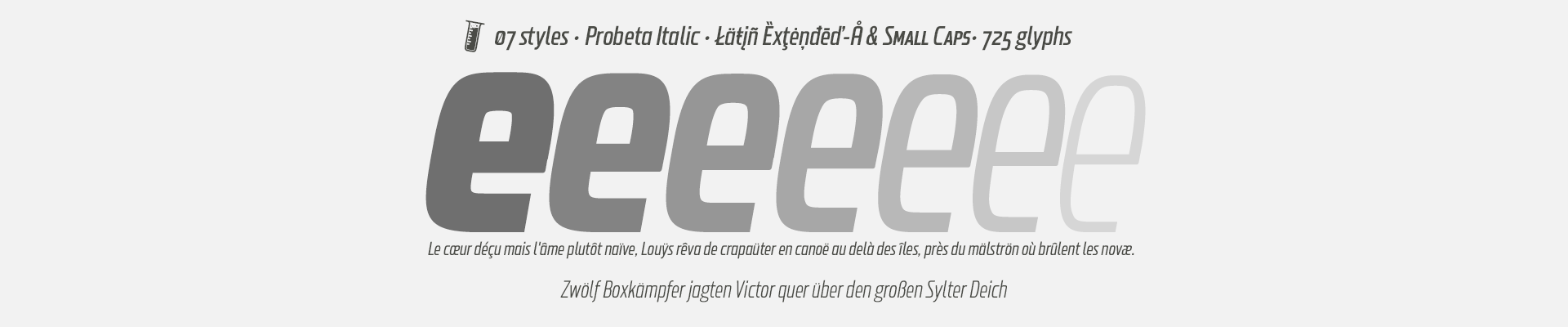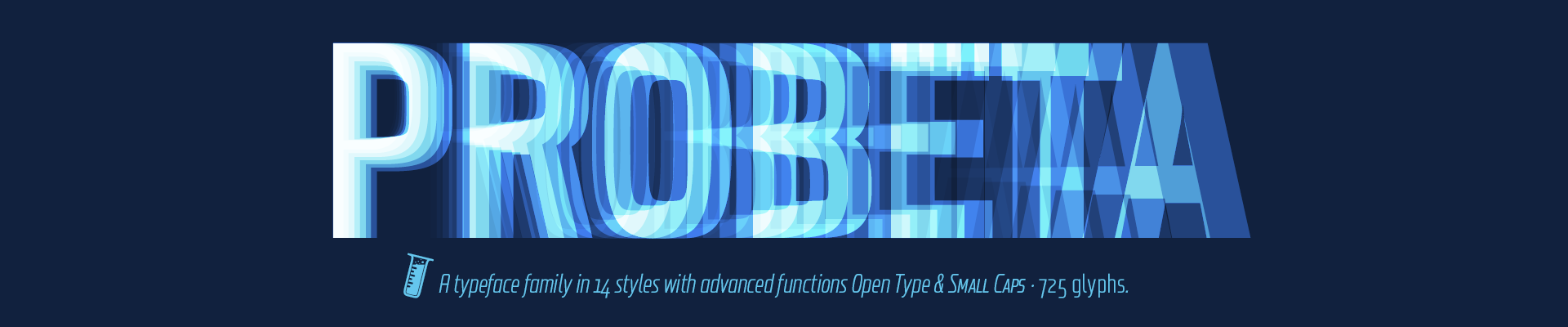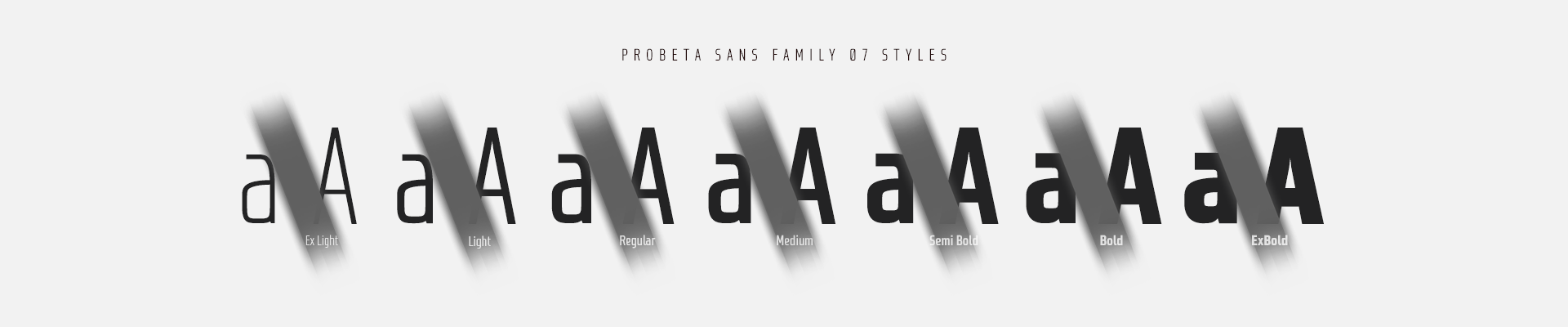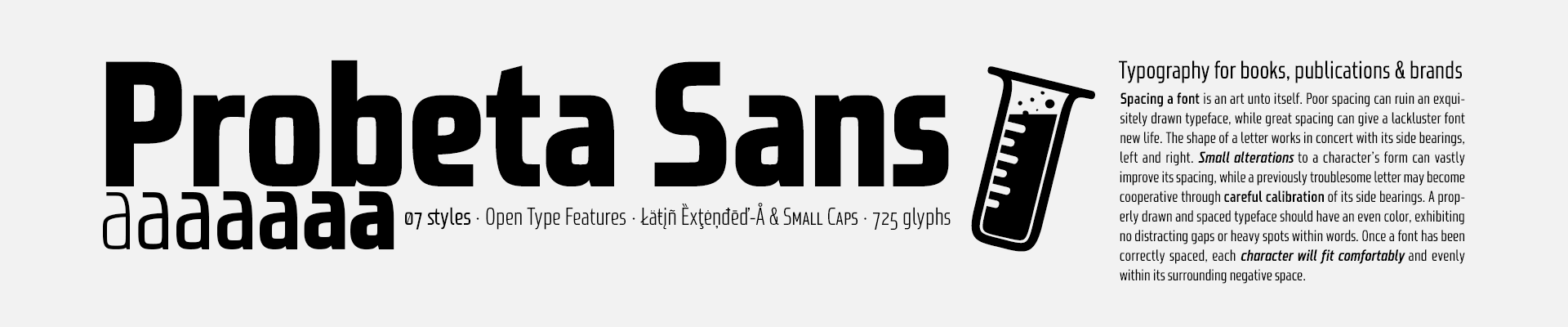
Después de definir todas las proporciones de la nueva tipografía, y partir del dibujo de la letra «o» minúscula, en un ejercicio de construcción minimalista, he construido todos los caracteres, aportando con esta técnica, coherencia morfológica y una lectura equilibrada. He puesto especial interés en la definición de la anchura de cada carácter, en función de la relación con otros, a continuación, la configuración de las métricas y la exhaustiva definición del Kerning, aportan máxima legibilidad en textos de párrafo y títulos.
Todas las versiones tienen caracteres en Versalita, letras alternativas, varios juegos de números y funciones avanzadas OpenType.
Estilo: Sans Serif, Condensed, Small Caps, Roman & Italics
Proporción: Extra Light, Light, Regular, Medium, Semi Bold, Bold & Extra Bold
Glyphs: 725
Alternates: 70
Latin-Extended: Latín Básico, Europa Occidental, Central & Oriental.
Funciones OpenType: Additional languages, All Alternates, Alternate Annotation Forms, Bitcoin, Capital Spacing, Contextual Alternates, Denominators, Discretionary Ligatures, Extended Fractions, Historical Forms, Inferiors, Kerning, Localized Forms, Numerators, Oldstyle Figures, Ordinals, Scientific Inferiors, Slashed Zero, Small Capitals, Small Capitals From Capitals, Standard Ligatures, Stylistic Set, Subscript, Superior letters, Superiors, Superscript.
Después de definir todas las proporciones de la nueva tipografía, y partir del dibujo de la letra «o» minúscula, en un ejercicio de construcción minimalista, he construido todos los caracteres, aportando con esta técnica, coherencia morfológica y una lectura equilibrada. He puesto especial interés en la definición de la anchura de cada carácter, en función de la relación con otros, a continuación, la configuración de las métricas y la exhaustiva definición del Kerning, aportan máxima legibilidad en textos de párrafo y títulos.
El uso en diseño gráfico, editorial o publicidad garantiza originalidad y diferencia. Unas fuentes muy versátiles para carteles publicitarios, vídeo juegos, títulos de cine, logotipos, publicaciones, etc. Incluyen el símbolo del Bitcoin y otras Cripto Monedas.
Todas las versiones tienen caracteres en Versalita, letras alternativas, varios juegos de números y funciones avanzadas Open Type.PDF Specimen & The Cheat Sheet.
Las fuentes «Probeta Roman & Italic disponen en su versión comercial de un juego de 725 glifos (Latin Extended-A), todas las versiones con soporte para cualquier idioma europeo o centro europeo. Probeta Sans también incluyen funciones OpenType (Compatibles con InDesign, QuarkXpress, Photoshop e Illustrator.